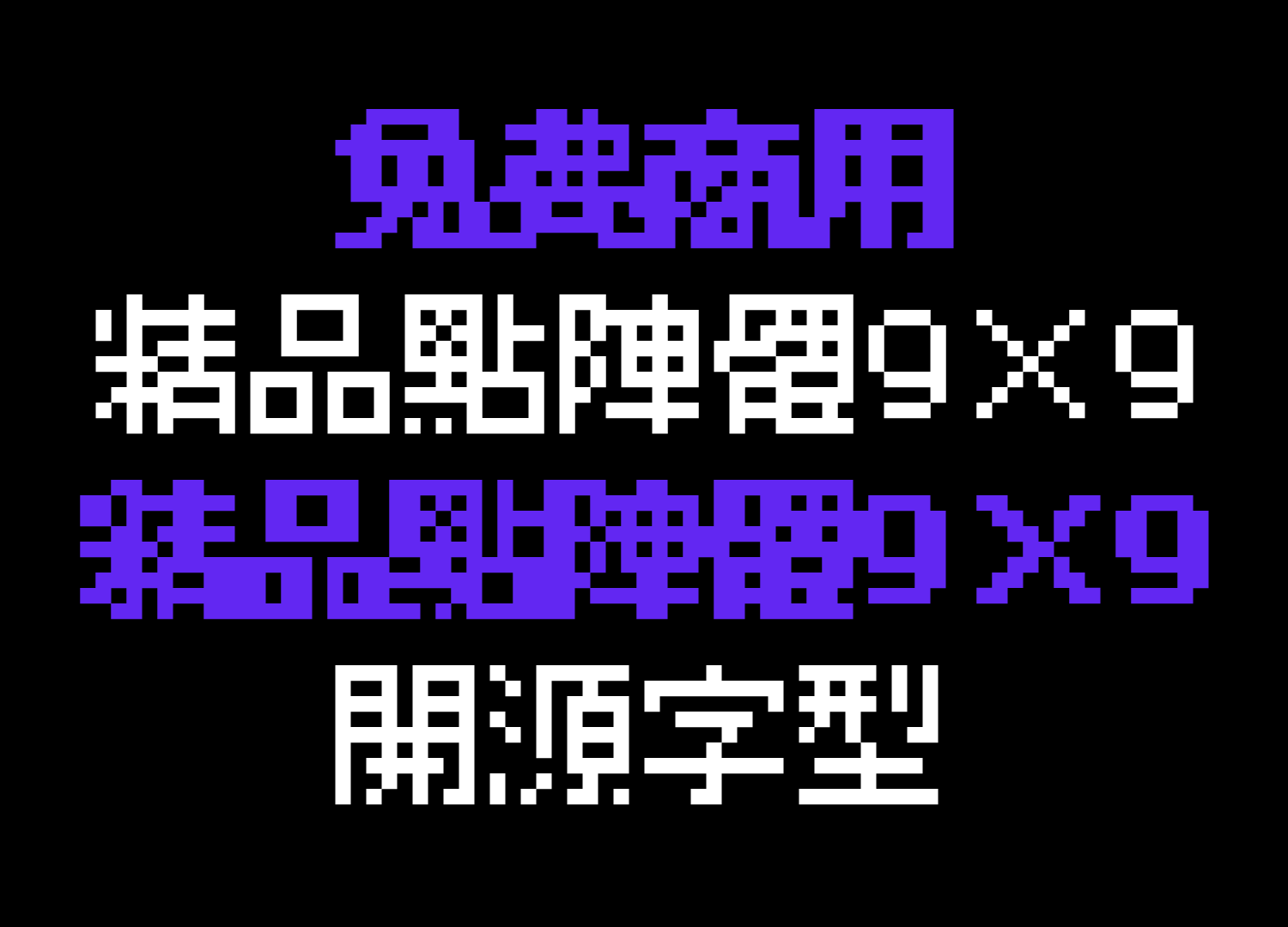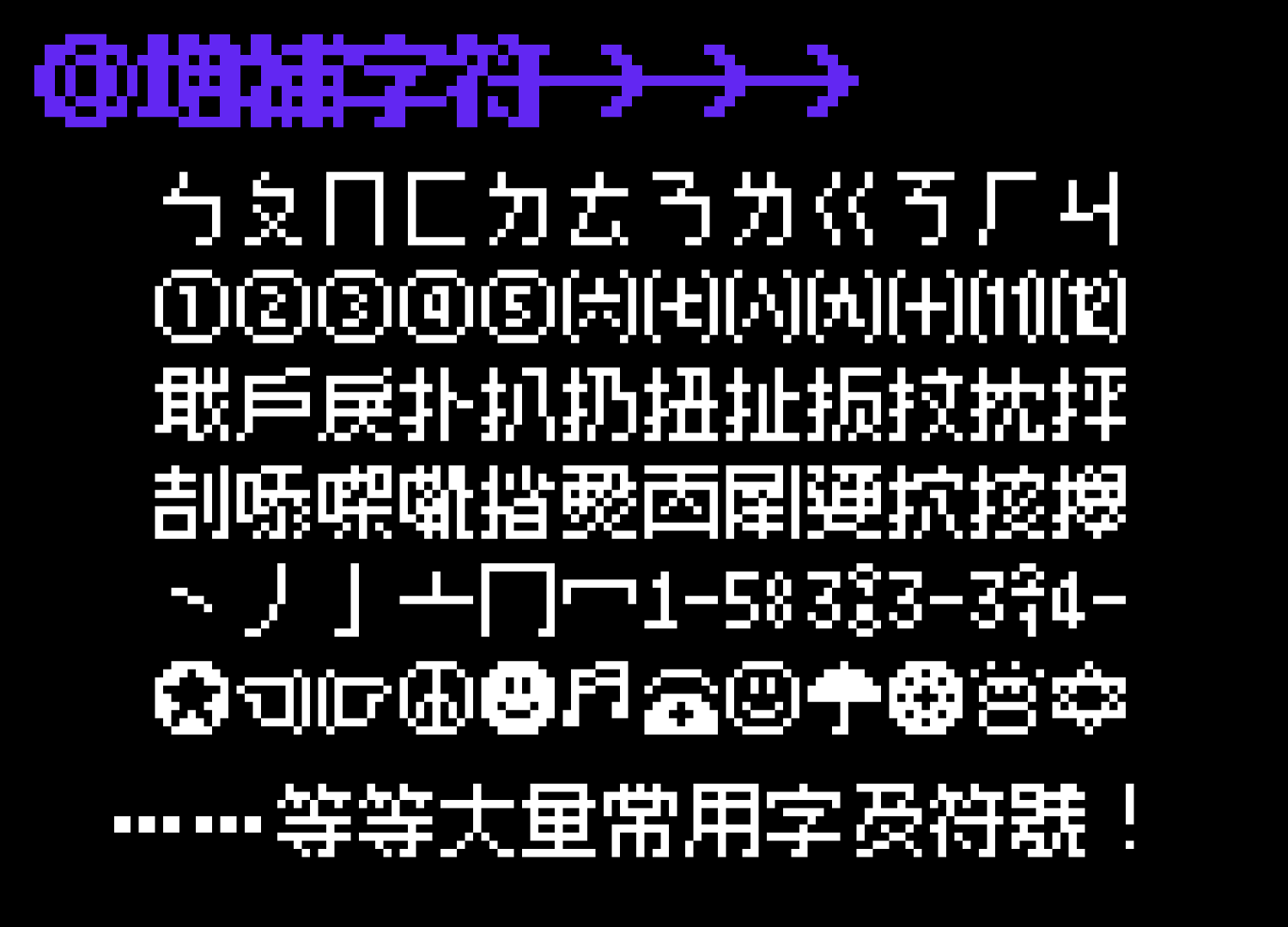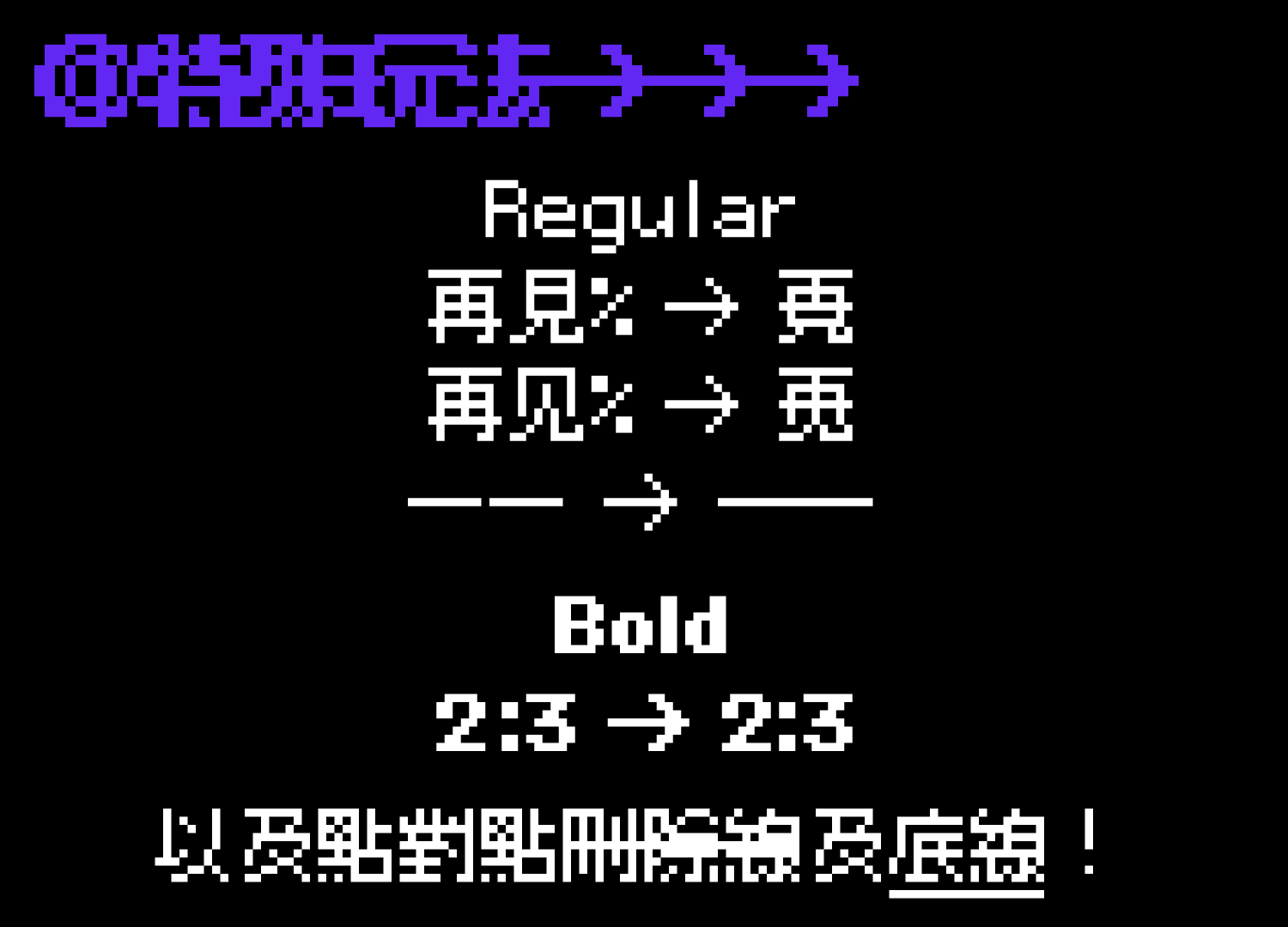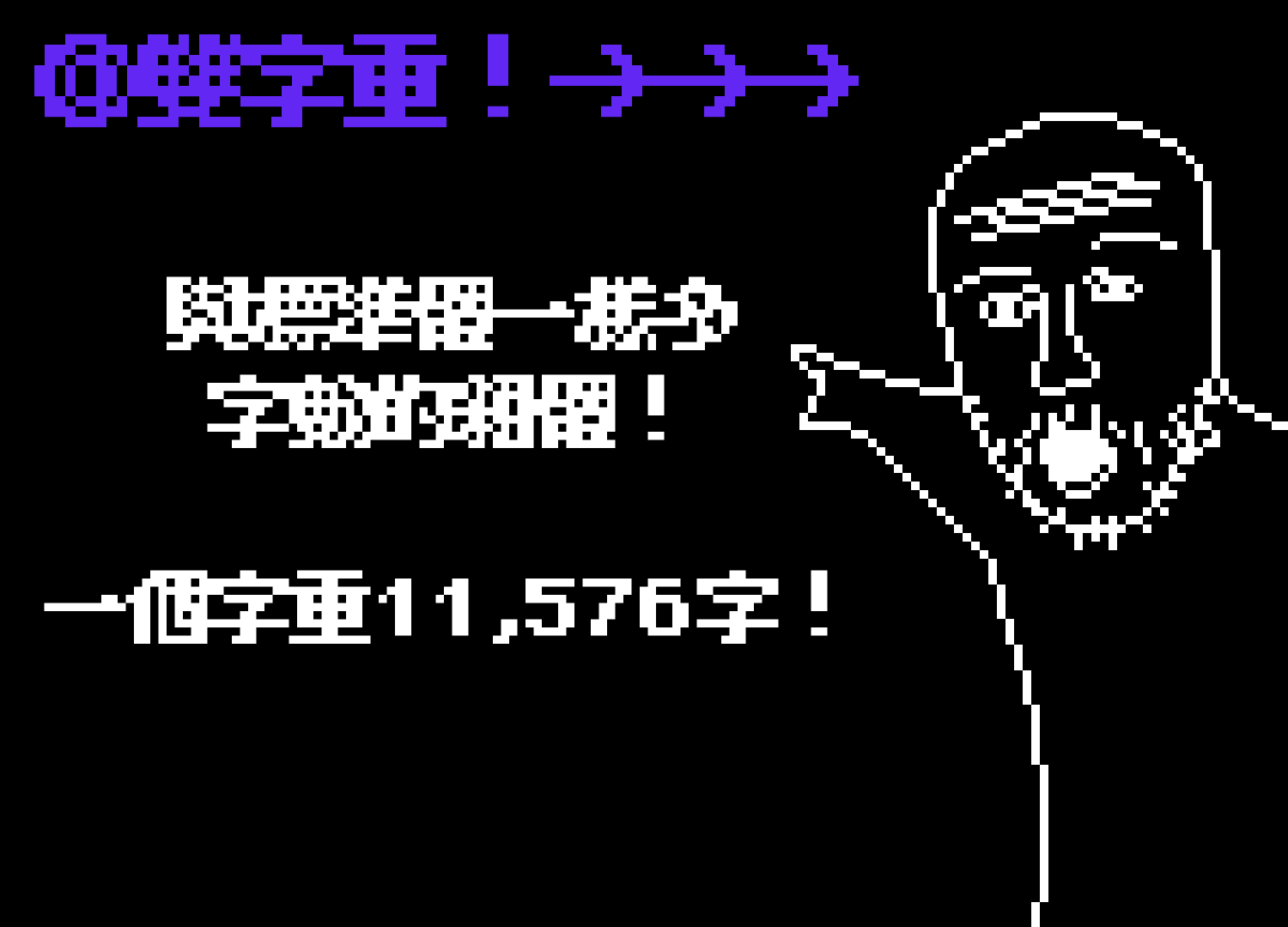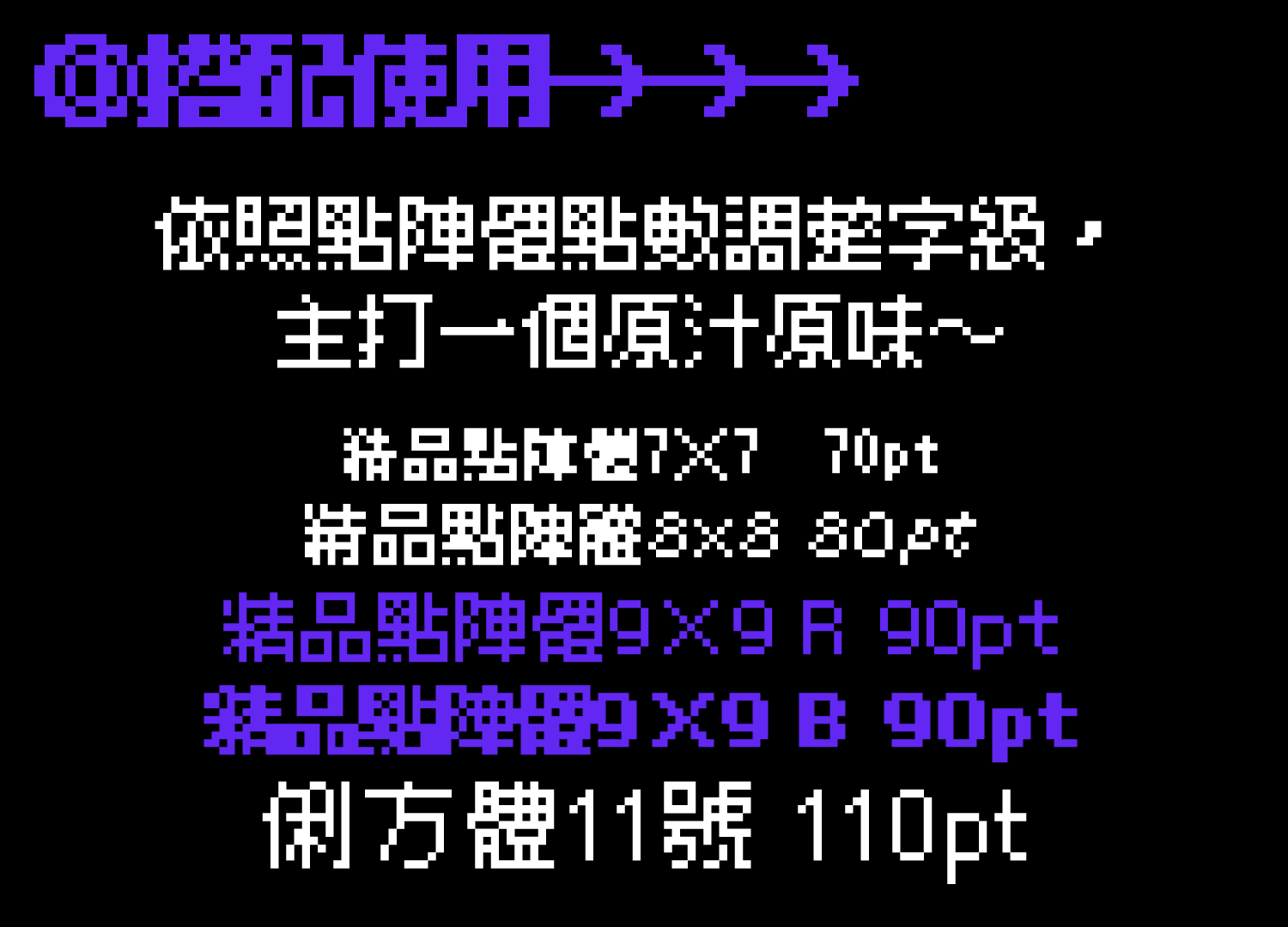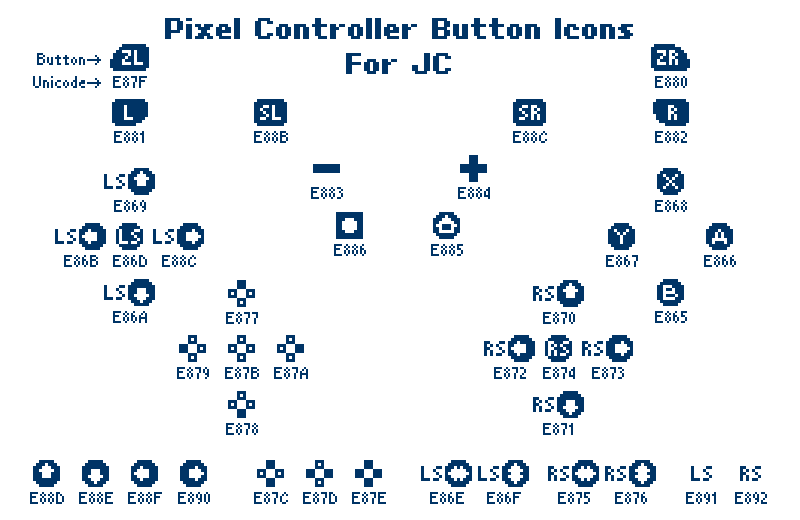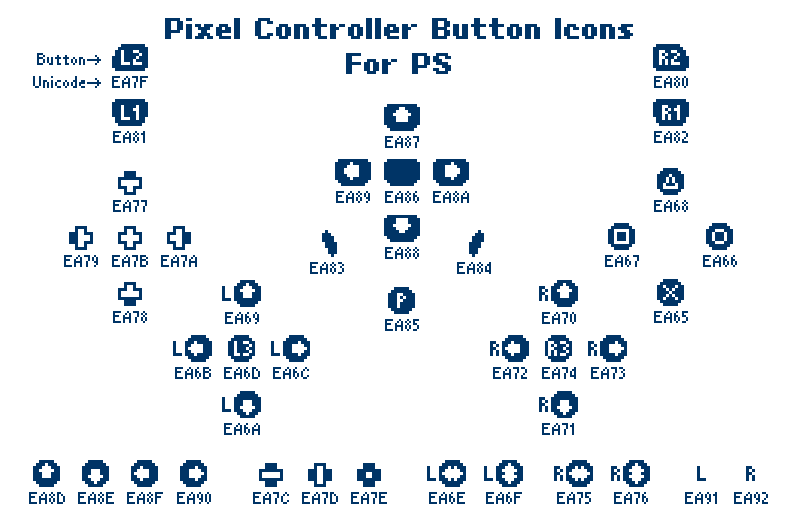
《精品点阵体 9×9 (BoutiqueBitmap9x9)》系列字型是基于 M+ BITMAP FONTS 以及ベストテン(BestTen-DOT)进行改造而制成的。该系列字型以缝合像素字体作为字符补充,旨在适用于繁体中文环境的使用。我们修复了一些标点符号的写法,增加了大量字符和 Opentype 特性——包括用于表情文字的符号、简体中文字符、直排特性等——使得该字型系列的使用更加便捷!
这是一种具有非常強烈点阵风格的字体,非常适合用于像素画、游戏相关主题等领域。
| BoutiqueBitmap9x9_1.93.ttf | 精品点阵体 9×9,评分为 1.93 分,评级为 R | 这是《精品点阵体 9×9》【普通版】,适用于绝大多数使用场景。该版本包含了游戏手柄按键字符,共计 12,858 个字符,包括繁体、简体以及台式中文和粤语常用字。其中,香港字的显示仅支持新版香港增补字符集(ISO 10646)的编码标准。 |
| BoutiqueBitmap9x9_Bold_1.93.ttf | 精品点阵体 9×9,尺寸为 1.93 B | 这是《精品点阵体 9×9》【普通版粗体】,说明与之前的一样。 |
| BoutiqueBitmap9x9HK_1.93.ttf | 精品点阵体 9×9 港 1.93 R | 这是《精品点阵字体 9×9》【香港版】,文字数量与普通版相同。该字体中的香港字符同时支持新旧版本的香港增补字符集(GCCS+HKSCS+ISO 10646)编码,适用于那些无法处理基本多文种平面外字符的系统和软件。由于与早期版本的精品点阵字体 9×9 游戏手柄按钮字符存在冲突,因此对香港版字体的游戏手柄按钮编码进行了修改。具体的修正方法请参考《游戏手柄按钮字符》香港版说明。 |
| BoutiqueBitmap9x9HK_Bold_1.93.ttf | 精品点阵体 9×9 港 1.93 B | 这是《精品点阵体 9×9》【香港版粗体】的说明,其手柄按键的字符编码与之前版本相同。 |
游戏手柄按钮字符
该字体包含了 3 种主流游戏主机手柄的按钮符号,方便开发者使用。具体的按钮 Unicode 编码及展示效果如下:
- JC:
- XC:
- PS:
- 示范:
| 港版说明: |
|---|
| 为了适应香港增加的字符集编码,我们特别调整了所有游戏手柄按钮的字符编码。所有的修改如下: |
| 【对于 JC 系统而言】所有以 E8 开头的按键现在都被修改成了以 EF 开头的样式。 例如:原本的“A”键对应的是“E866”,而港版字体则表示为“EF66”。 |
| 【对于 XB 来说】原本以 E9 开头的所有按键现在都改为以 F0 开头。 例如:原本的 B 键对应的是 E966,而港版字体则对应为 F066。 |
| 【适用于 PS 平台】原本以 EA 开头的按键全部被修改为以 F1 开头。 例如:原本的○键对应的是 EA66,而港版字体则对应 F166。 |